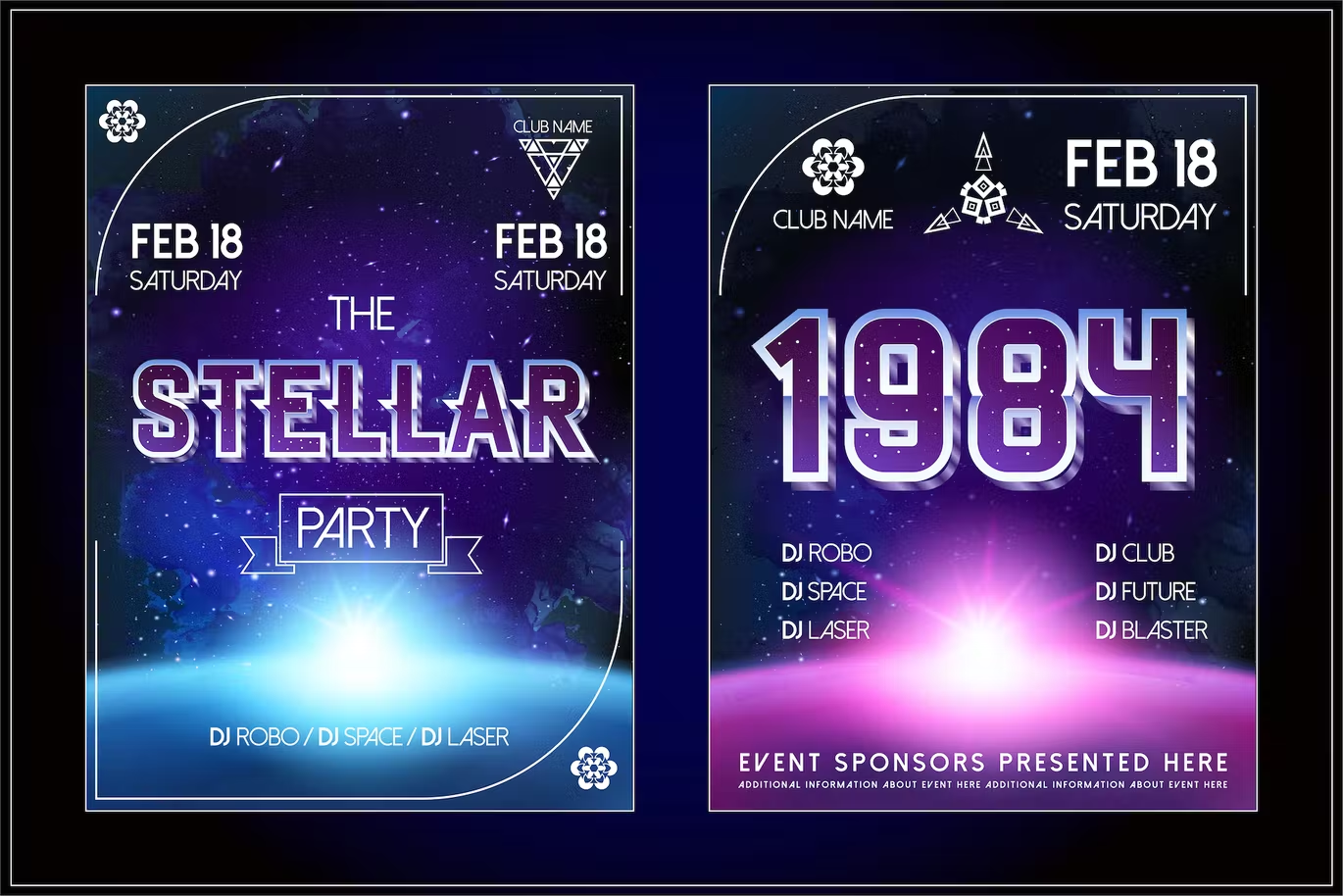
Retrowave Poster Font
Description de Retrowave Poster Font
Ce pack contient la tendance Vapor wave, Synth wave, Retro wave Styled Color OpenType Font au format de fichier .OTF avec des lettres, des chiffres et des signes de ponctuation (Adobe Illustrator 2018+).